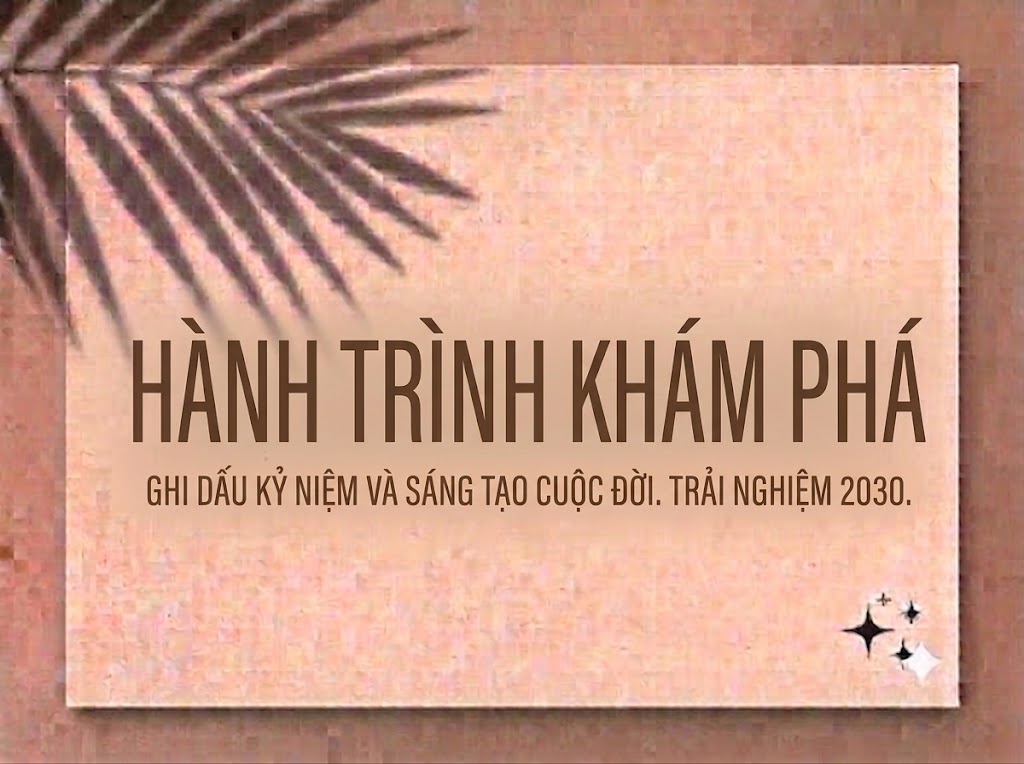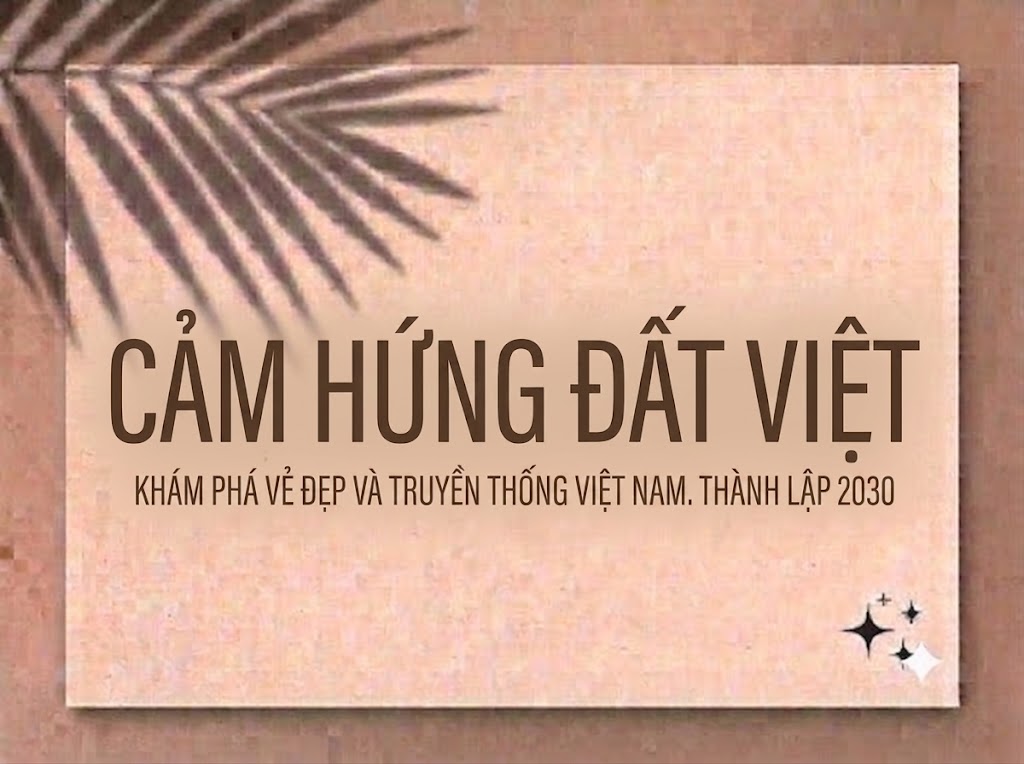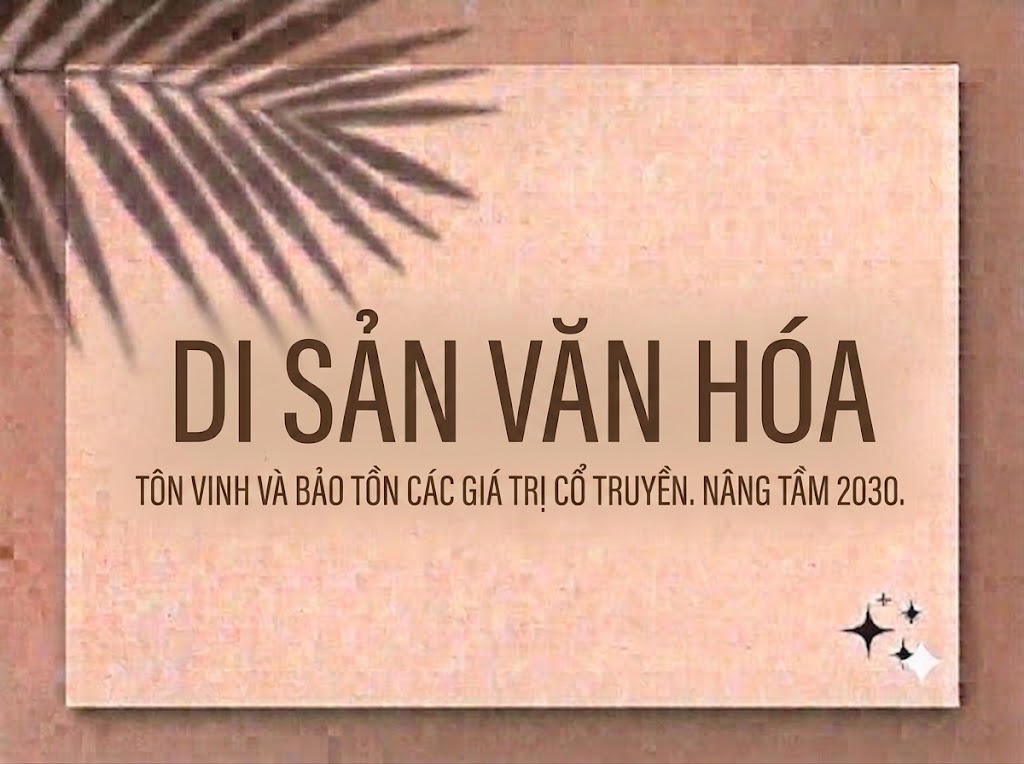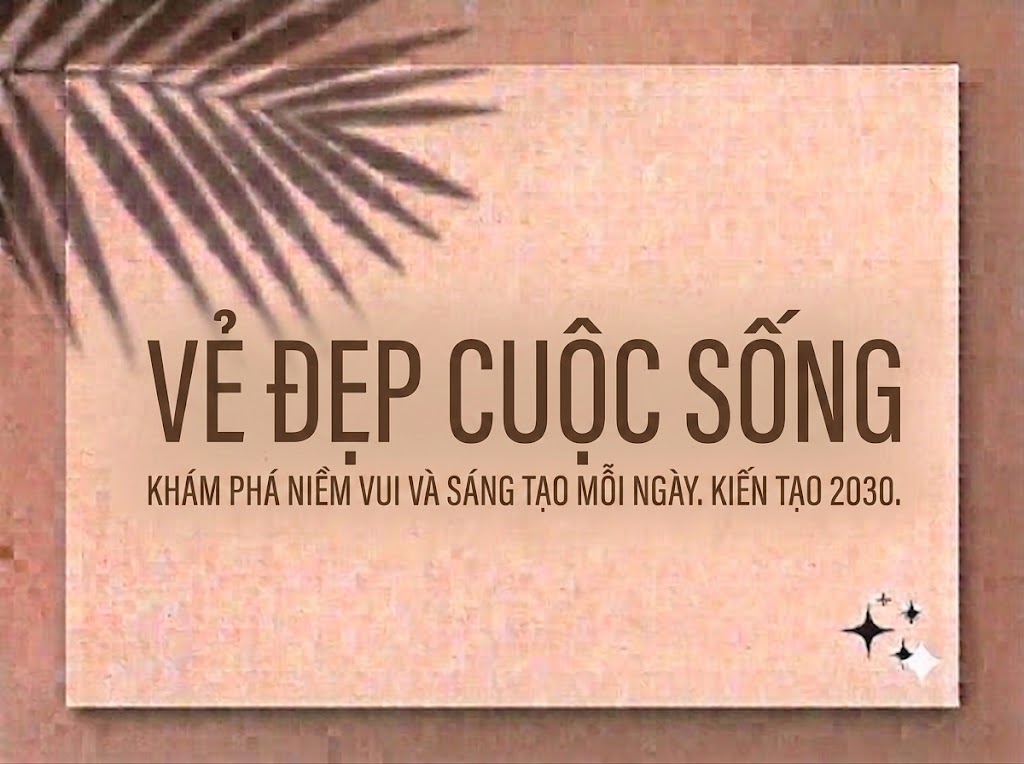
1FTV Freshwort
Trong thiết kế đồ họa đương đại, xu hướng tối giản (minimalism) kết hợp với các đường nét bo cong tròn trịa dạng hình học (geometric) luôn mang lại hiệu quả thị giác tuyệt vời. Những kiểu chữ này không chỉ mang đến cảm giác hiện đại, trẻ trung mà còn sở hữu độ nhận diện cực cao nhờ cấu trúc sạch sẽ và cân đối.
Nếu bạn đang tìm kiếm một bộ chữ không chân đa năng, vừa có nét mềm mại, gần gũi nhưng vẫn giữ được sự chuyên nghiệp để làm tiêu đề, phụ đề video hay thiết kế thương hiệu, thì font 1FTV Freshwost chính là một mảnh ghép hoàn hảo.
Giới thiệu về font 1FTV Freshwost
Font 1FTV Freshwost là một bộ chữ hiển thị không chân (sans-serif) được xây dựng trên những tỷ lệ hình học chuẩn mực, mang phong cách thiết kế hiện đại, tinh gọn và tràn đầy năng lượng tích cực.
Đặc điểm nổi bật của phong cách thiết kế Freshwost
Sức hút lớn nhất của font 1FTV Freshwost đến từ sự cân bằng hoàn hảo giữa tính cấu trúc hình học đứng dáng và những đường cong tự nhiên, thân thiện:
Tỷ lệ hình học (Geometric) chuẩn mực: Các ký tự tròn như o, c, d, q, p được tạo hình gần như những đường tròn hoàn hảo, mang lại cảm giác cực kỳ thông thoáng, ngăn nắp và hiện đại.
Độ dày nét đồng đều (Low Contrast): Độ tương phản thanh đậm của nét chữ rất thấp, tạo ra một kết cấu chữ vững chãi, đồng nhất. Đặc điểm này giúp cải thiện tối đa độ rõ nét (legibility), giúp người xem dễ dàng đọc được thông tin ngay từ những giây đầu tiên.
Hỗ trợ hệ ký tự hoa – thường đồng bộ: Freshwost tích hợp đầy đủ cả hệ thống chữ cái viết hoa và chữ viết thường, cho phép các nhà thiết kế tự do phối hợp linh hoạt để tạo ra nhịp điệu đọc tự nhiên và thoáng mắt nhất.
Hệ thống khoảng cách chữ (kerning) và độ giãn dòng (tracking) đã được căn chỉnh chuẩn xác, giúp các ký tự khi đứng cạnh nhau luôn giữ được khoảng trống thẩm mỹ lý tưởng, không bị dính nét hay gây ngột ngạt cho người đọc.
Tích hợp đầy đủ dãy số từ 0-9 dáng đứng ngay ngắn cùng hệ thống các ký tự đặc biệt, dấu câu thông dụng (
Bản Việt hóa chuẩn chỉnh giúp các nhà sáng tạo hoàn toàn yên tâm thiết kế các văn bản tiếng Việt có dấu phức tạp mà không lo gặp phải tình trạng nhảy font hay lỗi hiển thị dấu câu khó chịu.
Kích thước nhỏ (12pt – 24pt): Nhờ cấu trúc không chân thông thoáng và tỷ lệ hình học rõ ràng, bộ chữ thường vẫn hiển thị vô cùng ngay ngắn, sắc nét và cực kỳ dễ đọc ngay cả trên màn hình điện thoại di động cỡ nhỏ.
Kích thước lớn (36pt – 72pt): Đây là đất diễn lý tưởng nhất để font chữ phô diễn toàn bộ sự trẻ trung, hiện đại của cấu trúc hình khối tròn trịa, tạo tác động thị giác sạch sẽ và chuyên nghiệp cho các dòng headline chính.
Sở hữu nét cá tính hiện đại, sạch sẽ và cấu trúc hoa – thường linh hoạt, font 1FTV Freshwost mở ra không gian ứng dụng vô cùng rộng lớn cho các dự án truyền thông thế hệ mới:
Làm tiêu đề và phụ đề video ngắn (TikTok, Reels, Shorts): Dáng chữ đứng ngay ngắn, rành mạch cực kỳ hoàn hảo cho các khung hình dọc tỷ lệ 9:16. Độ rõ ràng của nét chữ giúp lời thoại phụ đề hay dòng giật tít hiển thị một cách tự nhiên, cuốn hút người xem lướt feed dừng lại ngay lập tức mà không che khuất các chủ thể chính của video.
Thiết kế ảnh thu nhỏ mạng xã hội (Thumbnail): Lựa chọn tuyệt vời cho các thumbnail YouTube, TikTok quảng cáo sản phẩm, nội dung phong cách sống, vlog gia đình, chia sẻ kiến thức hoặc e-commerce nhằm bứt phá tỷ lệ nhấp chuột (CTR) nhờ độ hiển thị trực diện từ khoảng cách xa.
Banner quảng cáo và nhận diện thương hiệu tối giản: Phù hợp làm logo dạng chữ khối, biểu ngữ quảng cáo, menu cửa hàng hoặc thiết kế nhãn mác, bao bì cho các thương hiệu F&B, local brand thời trang trẻ em, đồ gia dụng thông minh hoặc thiết bị công nghệ hướng tới sự tinh tế, thân thiện.